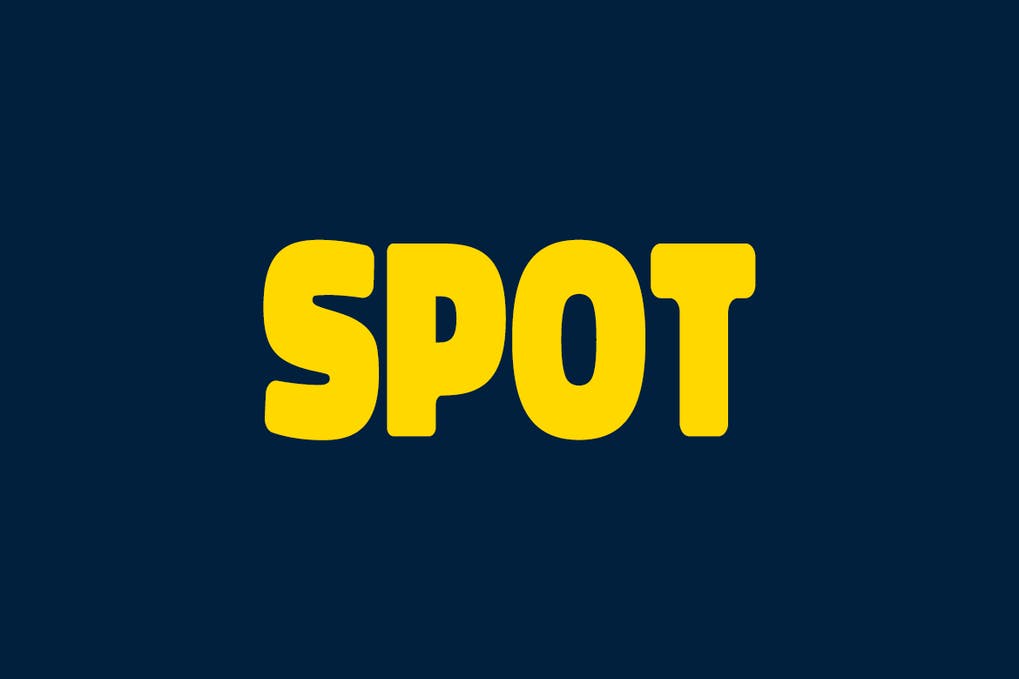
SPOT - Unique Display / Headline / Logo Typeface
SPOT - Affichage unique / Titre / Police de caractères du logo
SPOT est une police de caractères unique et moderne en majuscules pour les titres, les gros textes, la marque, les logotypes et l'utilisation de l'affichage. Cette police est également parfaite pour créer des logos exceptionnels, du contenu promotionnel et des graphiques marketing qui peuvent vraiment attirer l'attention de vos visiteurs. Veuillez consulter les exemples ci-dessus pour avoir une idée de la capacité de cette police de caractères.
SPOT est livré avec une seule graisse mais 4 styles (Regular, Italic, Outline Italic). Le pack contient OTF, TTF comme polices de bureau et des polices Web facultatives (tous les formats EOT, SVG, TTF, WOFF, WOFF2 inclus).